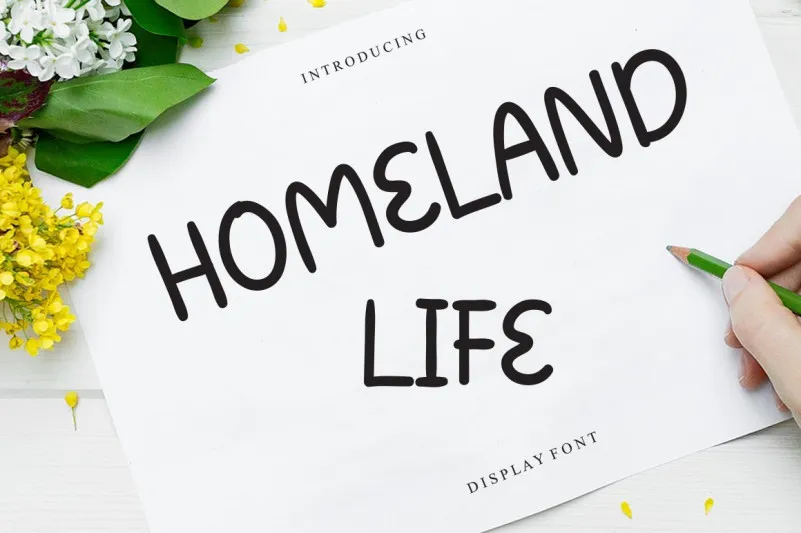
Homeland Life Font – Download Grátis
A Homeland Life Font é uma fonte desenhada à mão livre que combina simplicidade com adaptação versátil. Seu estilo natural e único a torna perfeita para um grande número de design, seja ele digital ou impresso. Com essa fonte bonita você pode explorar inúmeras variações e personalizações. É uma ótima opção para aqueles que desejam adicionar uma pitada de originalidade em seus projetos, sem sacrificar a simplicidade e clareza dos títulos ou headlines. Seja ela o título da sua revista de luxo, o nome do seu novo restaurante ou até mesmo a capa do seu próximo livro de receitas, a Homeland Life Font é uma escolha inteligente para expressar a essência do que você deseja transmitir. Engajue-se com essa linda fonte e descubra os muitos caminhos por onde ela pode levar seus projetos criativos.